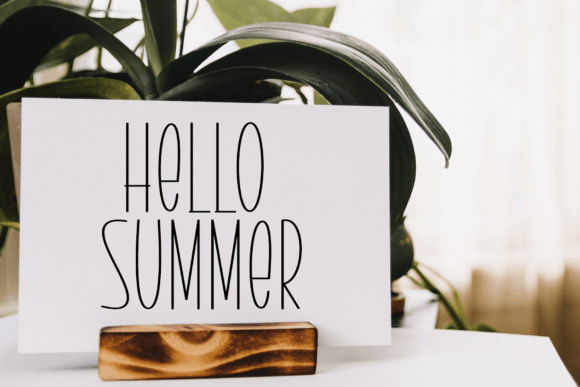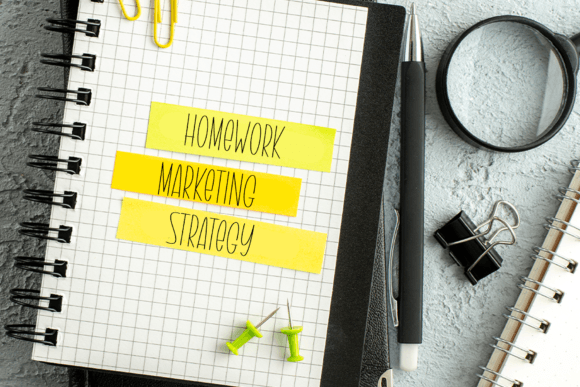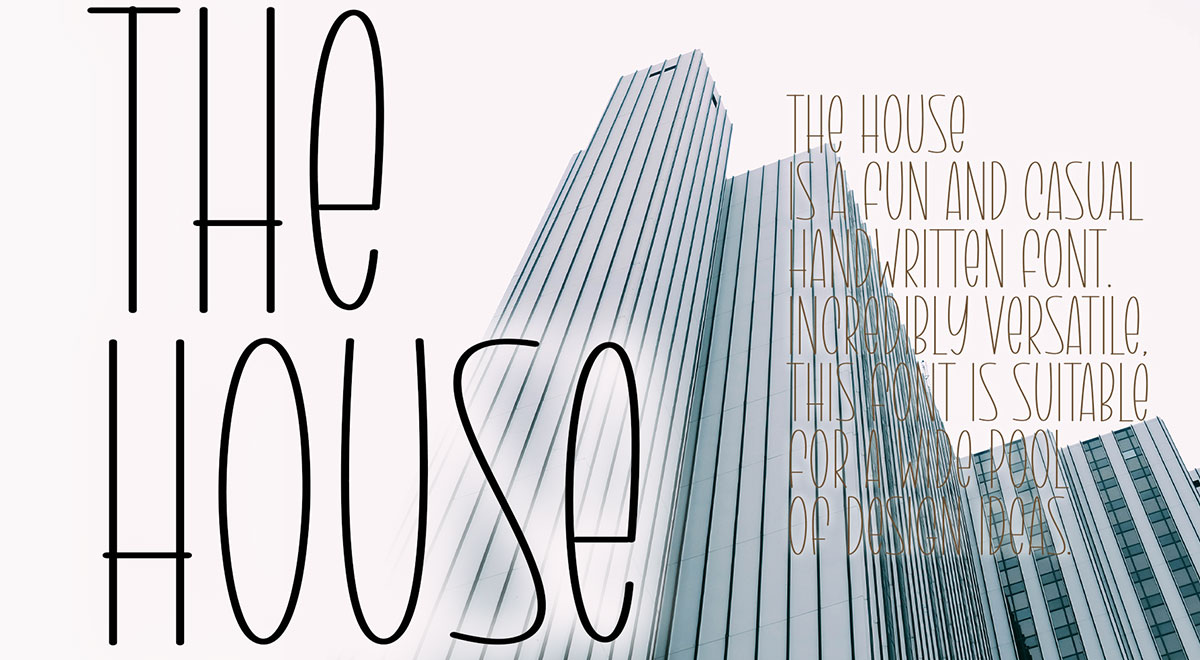
فونت The House انگلیسی
| ⭐ توضیحات | با معرفی The House Font، یک تایپ بدون سری شیک و مدرن که تجسم سادگی و تطبیق پذیری است. این فونت با خطوط تمیز و نسبت های متعادل خود ظاهری بی انتها و پیچیده را ارائه می دهد. این فونت که برای برندسازی، طراحی سرمقاله و علامتگذاری ایدهآل است، ظرافت و حرفهای بودن را به پروژههای شما میآورد و در عین حال شفافیت و خوانایی را حفظ میکند. |